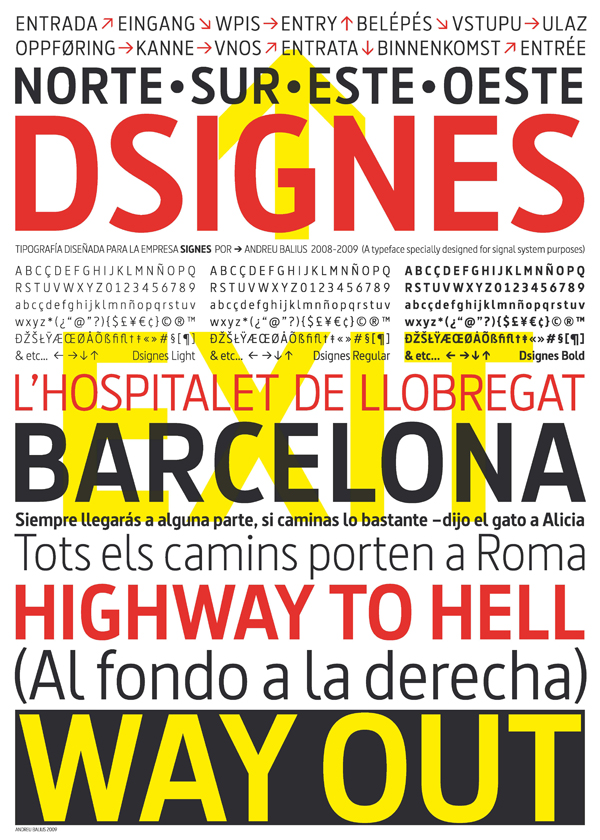
Dsignes, tipografía gratuita de Signes diseñada por Andreu Balius
Dsignes, tipografía libre de uso creada por Andreu Balius, para Signes, 2009.
El tipógrafo Andreu Balius crea para Signes, la empresa barcelonesa de fabricación e implantación de identidad corporativa, Dsignes, una familia tipográfica de libre uso destinada a ser empleada por el colectivo de arquitectos y diseñadores.
Diseñada especialmente para su aplicación en proyectos de señalización, Dsignes cuenta con tres pesos –light, regular y bold—y puede ser solicitada gratuitamente en latipodsignes@signes.es.
Este proyecto ha sido galardonado con el Premio Ed Awards (European Design Awards) 2010, y seleccionada para la muestra Desigñ en la Exposición de Shanghai 2010. Esta iniciativa se suma a las actividades de promoción y difusión del diseño de la Fundación Signes como la Designpedia o los Premios Signes.